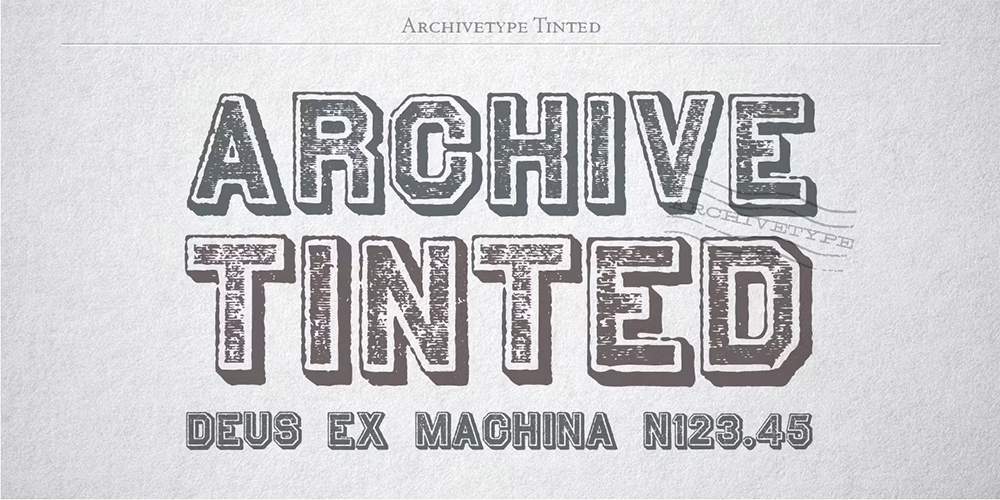
فونت پرمیوم و انگلیسی Archive Tinted Font يک فونت کثیف دوستداشتنی با ظاهری خشن است. اين فونت که کمی عجيب و غريب است، به هر يک از طرحهای شما جلوهای خاص میبخشد.
مزایای استفاده از فونت لاتین Archive Tinted چیست؟